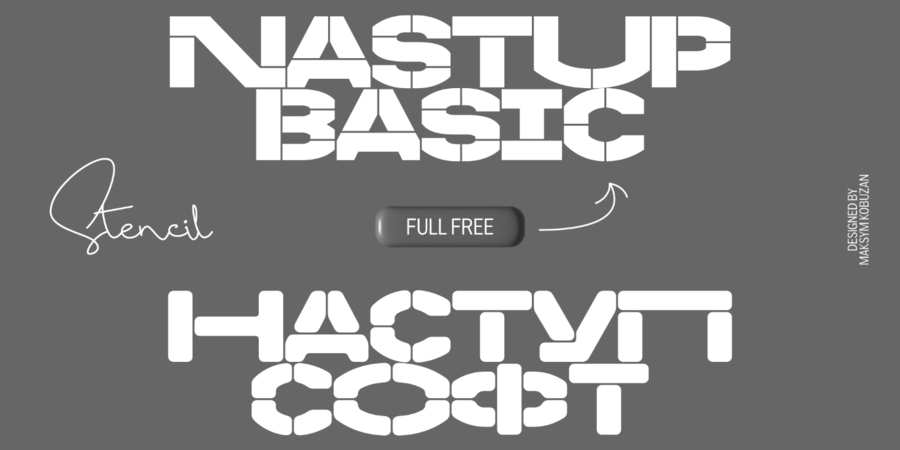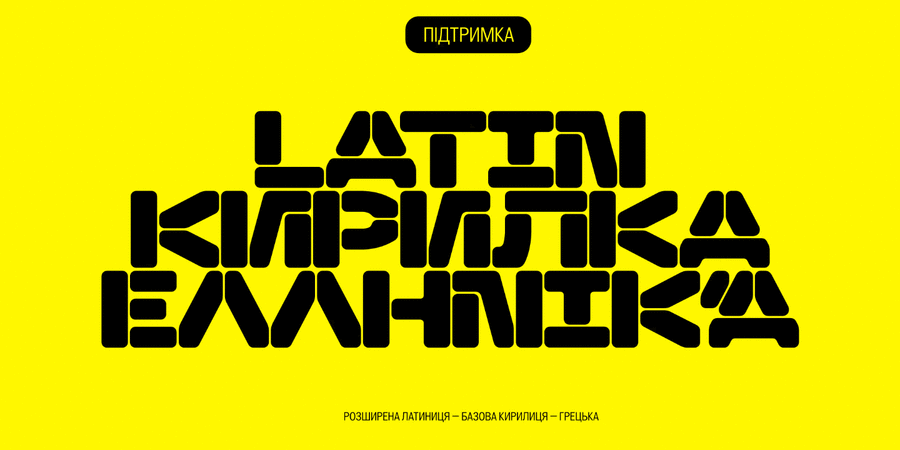
НАСТУП – це модульний трафаретний гротеск, натхненний трафаретними технічними знаками на стінах, а також різними будівельними деталями.
Особливістю графіки є зрізи овалів по боках. З таким мінімальним інтервалом це дає вужчий набір (особливо добре з мінімальним міжрядковим інтервалом). Також цей шрифт можна урізноманітнити альтернативними широкими або більш відкритими символами. Шрифт має 2 накреслення: стандартне BASIC та заокруглене SOFT.
НАСТУП володіє розширеною латиницею, базовою кирилицею, грецькою абеткою та розмовляє багатьма мовами. Крім того, він має альтернативний набір символів для української абетки.
Шрифт розробив Максим Кобузан у 2022 році.
Асоціації з сімейством шрифтів NASTUPОсобистість і характер гарнітури:
сильний, потужний, техногенний, важкий, твердий, жорсткий, гострий, сталевий, індустріальний, мужній, стійкий, статичний, міцний, значний, переконливий, авторитетний, наполегливий, рівний, чіткий, якісний, дзвінкий, прямокутний, серйозний, залізний, надійний, впевнений, військовий, армійський, солдатський, відповідальний, суворий, квадратний, точний, логічний, автоматичний, різкий, міський, машинний, інженерний, урбаністичний, промисловий, грізний, грубий, гучний, кондовий, сміливий, важливий, монументальний, тоталітарний, стабільний, робочий, мотивуючий, крутий, агресивний, залізничний, амбітний, брутальний, ігровий, нахабний, радикальний, спортивний, помітний, холодний, сучасний, креслярський, кінематографічний, гранчастий, тісний, чорний, ностальгічний, політичний, революційний, щільний, яскравий, активний, кричущий, гладенький, гумовий, пластмасовий
металургія, машинобудування, техніка, війна, танк, інструмент, будматеріали, будівництво, камінь, бетон, верстат, бодібілдинг, тренажери, завод, індустрія, промисловість, електростанція, енергетика, джинси, армія, ремонт, охорона, захист, страйкбол, блокбастер, бойовик, екшен, взуття, конструктор, креслення, архітектура, інженер, автоматика, урбаністика, Місто, авто, робот, гра, зброя, тара, склад, порт, ящик, патрони, депо, шолом, уніформа, вагон, автомат, шутер, спорт, екскаватор, позашляховик, шахта, шахтар, регбі, цегла, вантажівка, далекобійник, сталевар, мотор, двигун, залізо, технології, залізниця, робочий, кубики, лего, кіберспорт, Локдаун, комп'ютерна гра, селфі, нафта, автомобіль, паливо, вантажоперевезення, шоу, логістика, дизайн, авіація, кіно, супергерой, прапор, мітинг, політика, революція, страйк, Протест Гарнітура має ознаки стилів: